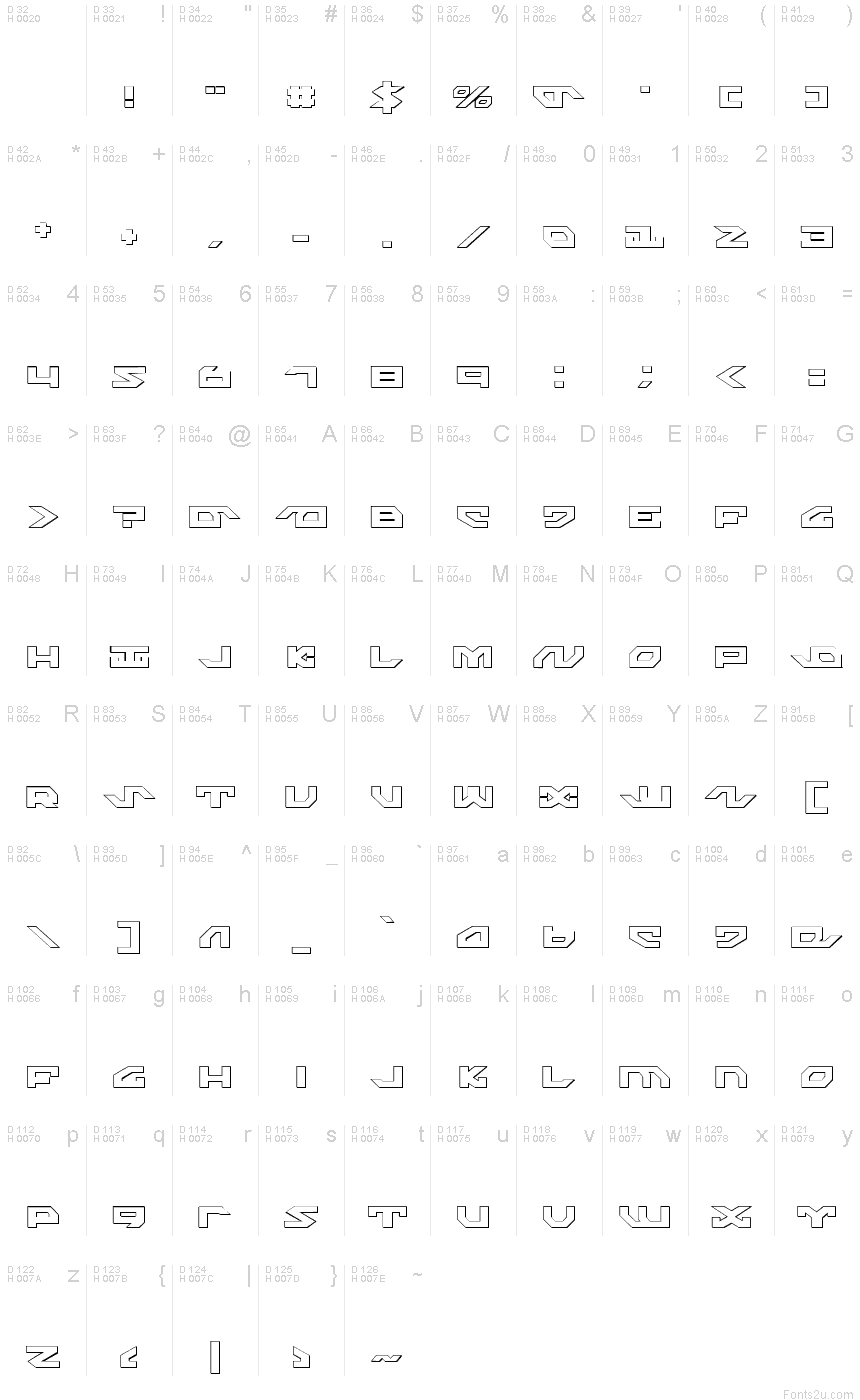
Nightrunner Shadow od Iconian Fonts to darmowy, futurystyczny font techno w wersji wersalikowej, o ostrym, arcade'owym charakterze. Litery wyglądają jak wykute z kanciastych torów i spiętrzonych narożników, z wyrazistą ramką zewnętrzną i przesuniętym cieniem wewnętrznym, co nadaje krojowi dynamiczny, mechaniczny rytm, daleki od łagodnych efektów sci-fi.
Dzięki temu ten darmowy font świetnie sprawdza się w logotypach gier, tytułach plakatów, okładkach mixtape’ów, miniaturach streamingowych i planszach tytułowych, gdzie krótkie słowa potrzebują szybkiego, syntetycznego pulsu. Działa również dobrze w przypadku monogramów i nagłówków, ponieważ cieniowana konstrukcja sprawia, że nawet kilka liter ma wystarczająco dużo ruchu i formy, by przyciągnąć wzrok na stronie.
Nightrunner Shadow od 2008 Iconian Fonts to darmowy font w wersji all-caps.
Glify zawierają wbudowany efekt przesuniętego cienia jako część znaków.
Nightrunner Shadow